たとえば「にゃー」という文字列を横組みにしたときと縦組みにしたときでは、小書きの「ゃ」と音引き「ー」の形が違っています。当たり前と言えば当たり前の挙動なので、普段あまり意識されることはないかもしれませんが、これもOpenTypeフィーチャーが実現していることのひとつです。
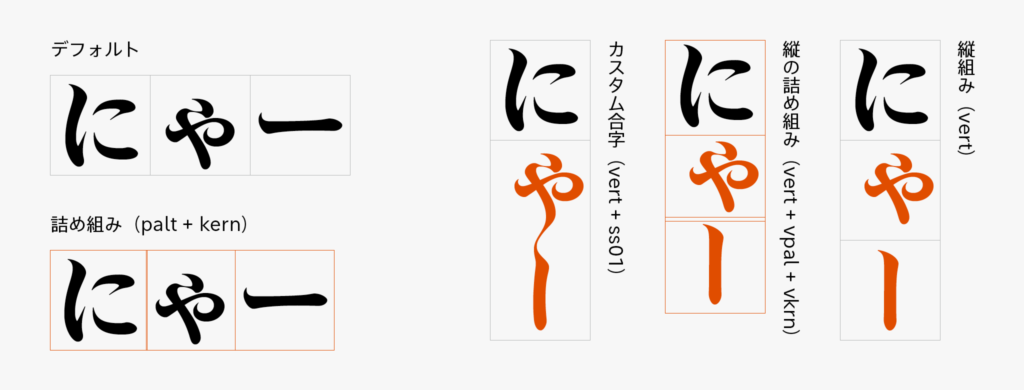
OpenTypeフィーチャーは、文字を読みやすく、あるいは美しく並べるために、OpenTypeフォントが内蔵している情報です。それぞれの機能には「フィーチャータグ」と呼ばれる英数字4文字の名前がついています。先ほどの縦組みの例では「vert」が参照されています。
縦組みのテキストでは「vert」は自動的に適用されますが、詰め組みのように、ユーザーの意図にしたがった組み体裁を実現するためにも、OpenTypeフィーチャーは使われます。
今回、図で用いているのは金シャチフォント 姫です。このフォントでは「ゃー」などの組み合わせに対して、カスタムグリフを選択できるようになっています。金シャチフォント 姫では、このようなカスタムグリフを表示するために「スタイルセット1(ss01)」というOpenTypeフィーチャーを使っています。